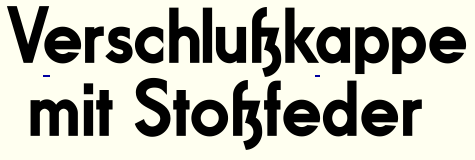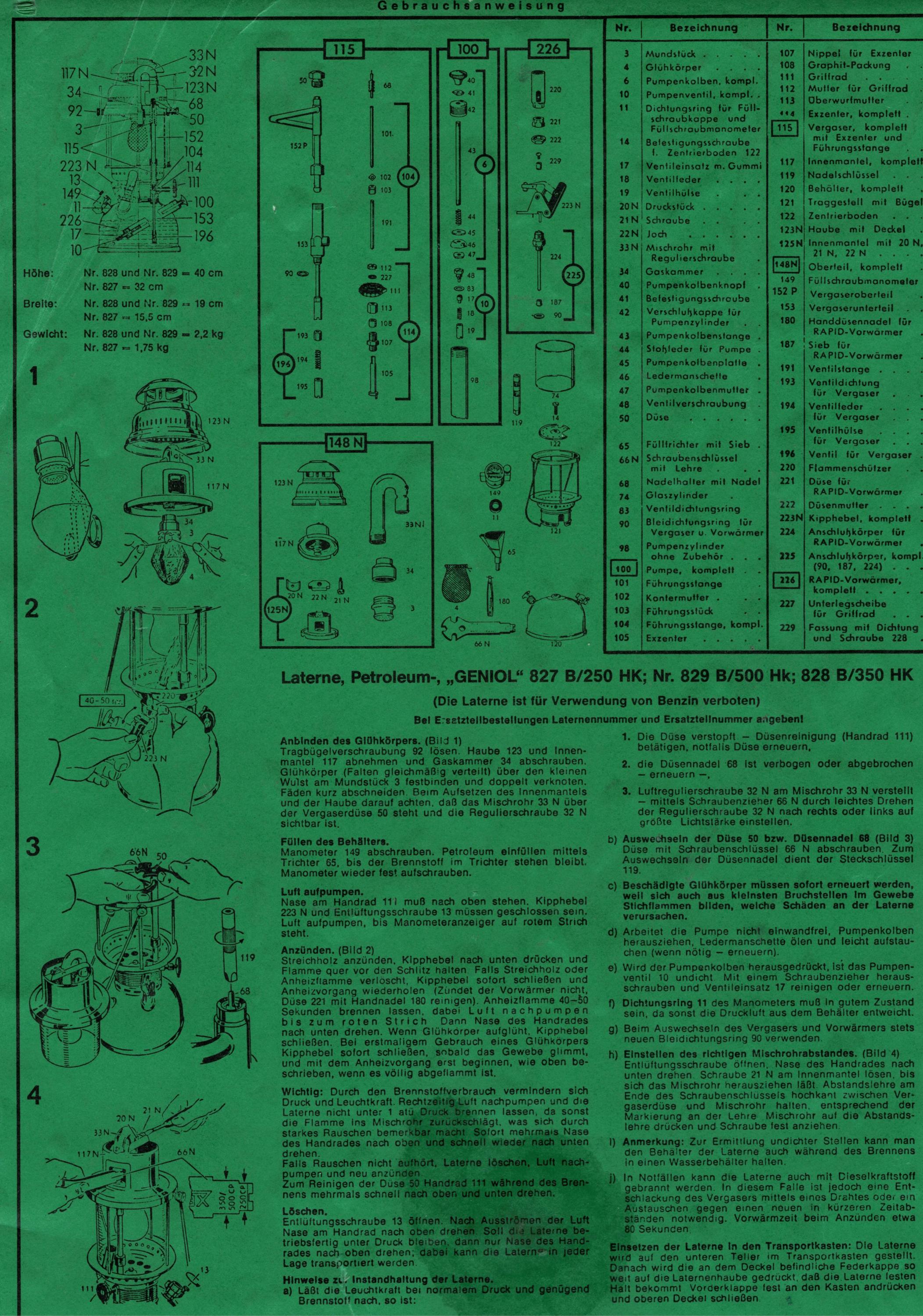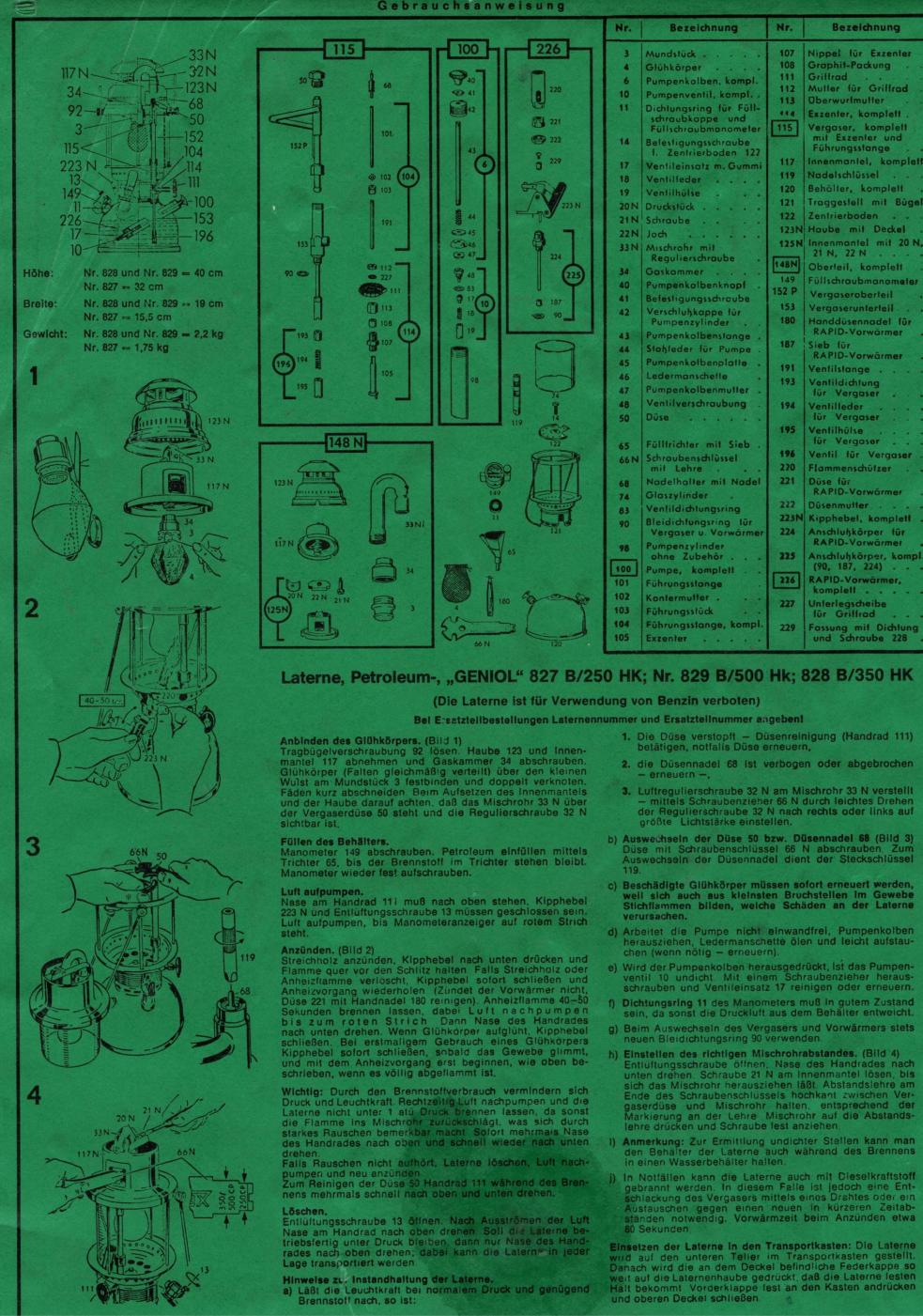
Schriftarten einer Petromax-Bedienungsanleitung von ca. 1960/1970 gesucht
ich möchte gerne eine Bedienungsanleitung für meine Petromax 1500 verfassen. Eine Petromax ist eine Petroleumstarklichtlampe welche z.B. ehemals in den Beständen der Bundeswehr zur Lichterzeugung genutzt wurden. Die entsprechenden Lampen der Bundeswehr nennen sich Petromax 829 B. Diese Lampen wurden speziell für das Militär gefertigt und waren anders als ihre zivilen Pendants mattiert und wurden in entsprechenden Aufbewahrungskisten verwahrt.
Eine Petromax 1500 wiederum ist zwar technisch stark verwandt mit einer solchen Bundeswehrlampe, allerdings wurden diese eher im zivilen Bereich als Heiz-/Kochgerät im Campingbereich eingesetzt.
Die Kisten der Bundeswehr-Petromaxe haben meist im Deckel eine Kurzanleitung integriert, welche die Bedienung der Lampe beschreibt. Für meine Lampe vom Typ 1500 habe ich nun ein Gehäuse aus Bundeswehrbeständen derart modifiziert, dass dieses statt der Bundeswehrvariante die Campingvariante aufnehmen kann. Nun würde ich gerne im Deckel ebenfalls eine Kurzanleitung für die Petromax 1500 anbringen. Leider gibt es soetwas bisher nicht und alle gescannten Varianten sagen mir bisher nicht zu. Deshalb würde ich gerne eine eigene Anleitung schreiben und müsste dafür aber wissen, welche Schriftart sich am ehesten eignet um dem Original möglichst nahe zu kommen.
Es scheinen mindestens zwei verschiedene Schriftarten in der angehängten PDF-Datei genutzt worden zu sein. Speziell in der Teileauflistung der markierte Punkt 44 ist hier zu nennen. Man erkennt dort ein altes ß im Wort "Stoßleder" welches ich in dieser Form in noch keiner Schrift finden konnte.
Können Sie mir bitte sagen, welche Schriftarten ich für eine Replik dieser Anleitung nutzen könnte? Da es sich um ein Hobbyprojekt handelt wäre mir natürlich sehr daran gelegen, dass die vorgeschlagenen Schriftarten nach möglichkeit kostenlos sind.
Man findet hier höher aufgelöste Abbildungen (PX_01.pdf und PX_02.pdf) sowie viele weitere Scans alter Bedienungsanleitungen etc., vielleicht hilft’s euch beim Erkennen: https://www.starklicht.com/downloads/
Die Futura war immer wieder beteiligt, auch eine Helvetica / Neue Haas o.ä.
Im Anhang habe ich die Anleitung nochmal in etwas höherer Auflösung als JPG angehängt.
Ich würde auch auf Helvetica, Akzidenz Grotesk und Futura tippen – alles keine kostenlosen Fonts.
Wenn es kostenlos und ähnlich sein soll:
Helvetica
https://de.wikipedia.org/wiki/Nimbus_Sans_L
bzw. hier mal stöbern:
Futura
http://www.peter-wiegel.de/Fundamental.html
https://fonts.google.com/specimen/Didact+Gothic
http://www.peter-wiegel.de/CAT_Neuzeit.html
Haben diese Schriftarten denn das genannte alte ß? Es sind ja vermutlich in der Hauptsache zwei verschiedene Schriftarten. Welche wäre dann der Haupttext und welche die Beschreibung mit dem ß?
das hat mir schonmal sehr geholfen, den Kasten auf der rechten Seite habe ich damit sehr gut befüllen können. Haben Sie eventuell auch entsprechende Vorschläge für den unteren Textblock und dessen Überschrift?